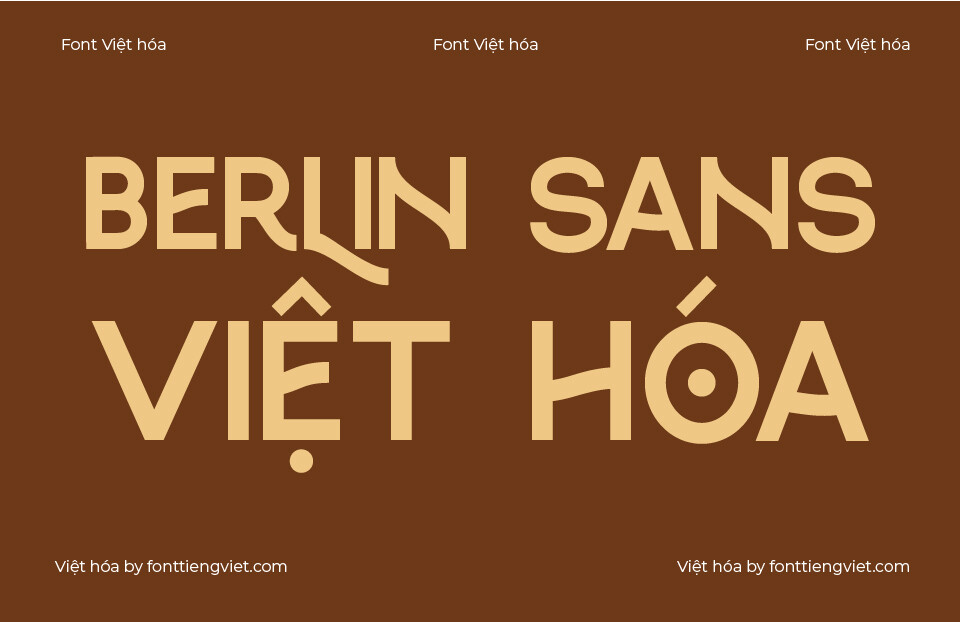
Font Việt hóa 1FTV VIP Berlin Sans
Giới thiệu về Font Việt hóa 1FTV VIP Berlin Sans
Trong thế giới đồ họa hiện đại, việc lựa chọn một bộ Font Miễn Phí chất lượng luôn là ưu tiên hàng đầu của các nhà thiết kế. Một trong những cái tên đang gây chú ý gần đây chính là Font Việt hóa 1FTV VIP Berlin Sans. Đây là phiên bản được tinh chỉnh kỹ lưỡng để phù hợp hoàn hảo với hệ thống bảng mã tiếng Việt, giúp loại bỏ hoàn toàn các lỗi hiển thị dấu phổ biến. Với phong cách Geometric Sans-Serif đặc trưng, bộ font này mang đến sự cân bằng tuyệt vời giữa nét cổ điển của những thập niên đầu thế kỷ 20 và sự tối giản, sang trọng của xu hướng thiết kế đương đại. Berlin Sans từ lâu đã nổi tiếng nhờ các đường nét bo tròn mềm mại nhưng vẫn giữ được cấu trúc khung chữ chắc chắn, tạo cảm giác thân thiện và dễ tiếp cận cho người xem.
Tại sao nên sử dụng Font Việt hóa 1FTV VIP Berlin Sans?
Thiết kế tinh tế và tính ứng dụng cao
Bộ Font Việt hóa 1FTV VIP Berlin Sans sở hữu các đặc điểm nhận diện rất riêng biệt như các nét cong mượt mà và khoảng cách giữa các ký tự được tính toán khoa học. Điều này giúp văn bản trở nên cực kỳ dễ đọc ngay cả ở kích thước nhỏ hoặc trên các màn hình có độ phân giải thấp. Đối với các bạn học sinh và sinh viên, việc sử dụng font chữ này trong các bài thuyết trình PowerPoint hoặc báo cáo học tập sẽ giúp nội dung trở nên chuyên nghiệp và thu hút hơn hẳn các bộ font mặc định nhàm chán. Trong môi trường học đường, sự rõ ràng của Berlin Sans hỗ trợ đắc lực cho việc trình bày giáo án điện tử, giúp học sinh dễ dàng theo dõi bài giảng mà không bị mỏi mắt.
Tối ưu hóa cho tiếng Việt
Điểm mạnh nhất của phiên bản 1FTV VIP chính là việc xử lý các dấu thanh và ký tự đặc biệt như “ă”, “â”, “đ”, “ơ”, “ư”. Các dấu được đặt ở vị trí hợp lý, không quá cao cũng không quá sát thân chữ, đảm bảo tính thẩm mỹ đồng nhất cho toàn bộ văn bản. Khi sử dụng Font Việt hóa 1FTV VIP Berlin Sans, bạn sẽ không còn phải lo lắng về tình trạng các chữ có dấu bị nhảy font hay lệch dòng, vốn là nỗi ám ảnh của nhiều người khi thiết kế bằng các bộ font nước ngoài chưa qua Việt hóa.
Ứng dụng Font Việt hóa 1FTV VIP Berlin Sans trong thực tế
Nhờ vẻ ngoài hiện đại và thanh lịch, bộ font này có thể ứng dụng đa dạng trong nhiều lĩnh vực khác nhau. Trong thiết kế thương hiệu, nó cực kỳ phù hợp để làm logo, tiêu đề bìa sách hoặc thiết kế bao bì sản phẩm cao cấp. Trong lĩnh vực truyền thông mạng xã hội, Font Việt hóa 1FTV VIP Berlin Sans giúp các banner quảng cáo hoặc ảnh trích dẫn (quotes) trở nên nổi bật và mang tính nghệ thuật cao. Đối với các thầy cô giáo, đây là lựa chọn tuyệt vời để thiết kế các phiếu bài tập sinh động, kích thích sự hứng thú học tập của học sinh qua những con chữ đẹp mắt và chỉn chu.
Tổng kết về bộ font chữ ấn tượng này